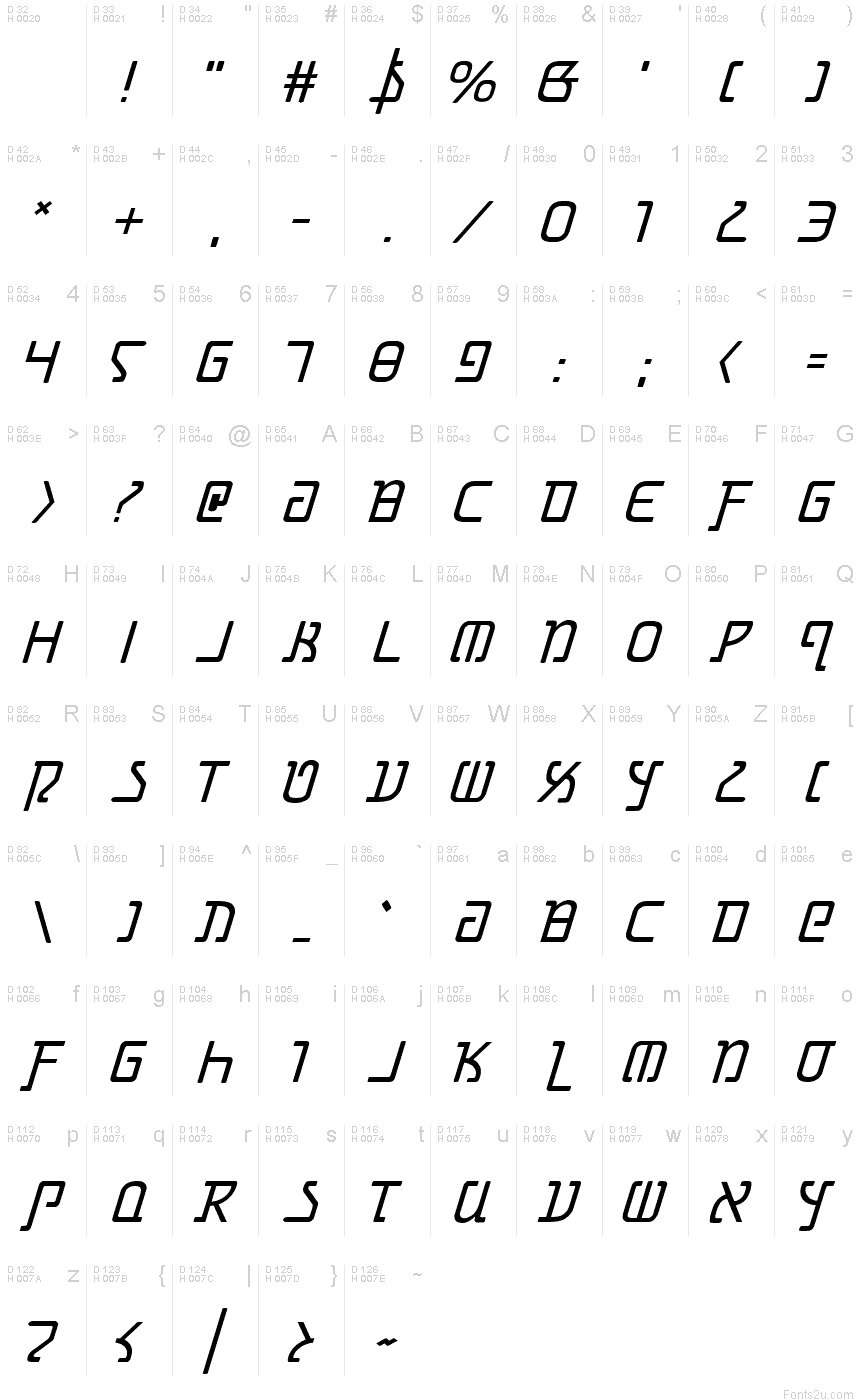
Grimlord Italic autorstwa Iconian Fonts to darmowy, kanciasty krój display o szybkim, futurystycznym nachyleniu. Jego ostro cięte wielkie litery łączą szerokie ukośne pociągnięcia, kanciaste łuki i otwarte połączenia, tworząc sylwetkę o mechanicznym charakterze.
Może zbudować przekonującą tożsamość science-fiction dla grafik w grach, brandingu e-sportowego i opakowań technologicznych, zwłaszcza gdy liternictwo ma sugerować prędkość lub zaprojektowany technicznie sprzęt. W publikacjach strome, dynamicznie skierowane do przodu formy pasują do nagłówków okładek magazynów oraz wstępów do artykułów poświęconych motorsportowi, gamingowi lub fantastyce spekulatywnej.